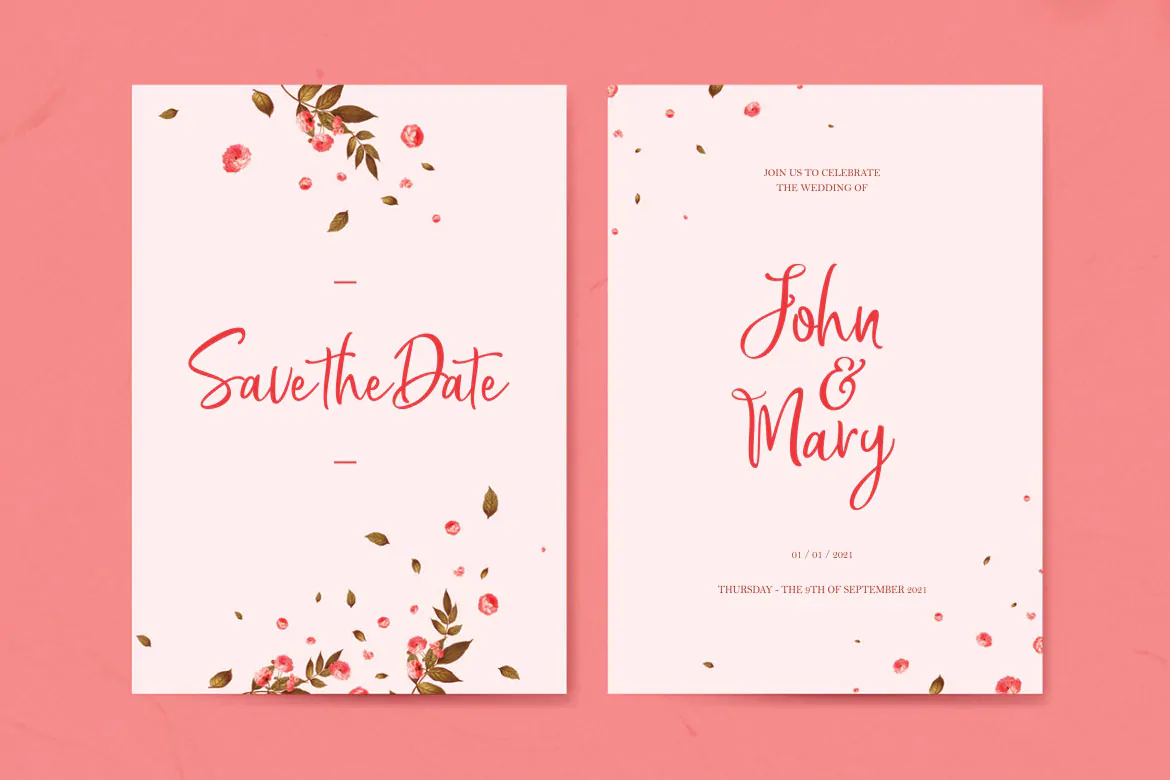
فونت یکسره نویسی جذاب و جالب Bread Store
فونت یکسره نویسی جذاب انگلیسی
فونت یکسره نویسی جذاب و جالب Bread Store یک اسکریپت فونت 2 تایی فوق العاده زیبای انگلیسی است که مناسب برای استفاده در پروژههای مختلف میباشد. این 2 قلم زیبا با وزن معمولی طراحی شدهاند که میتوان از آنها در طراحی انواع پوستر، بسته بندی محصولات، ظروف یکبار مصرف کاغذی، لوازم التحریر، پوستر، کارت ویزیت و … استفاده نمود.